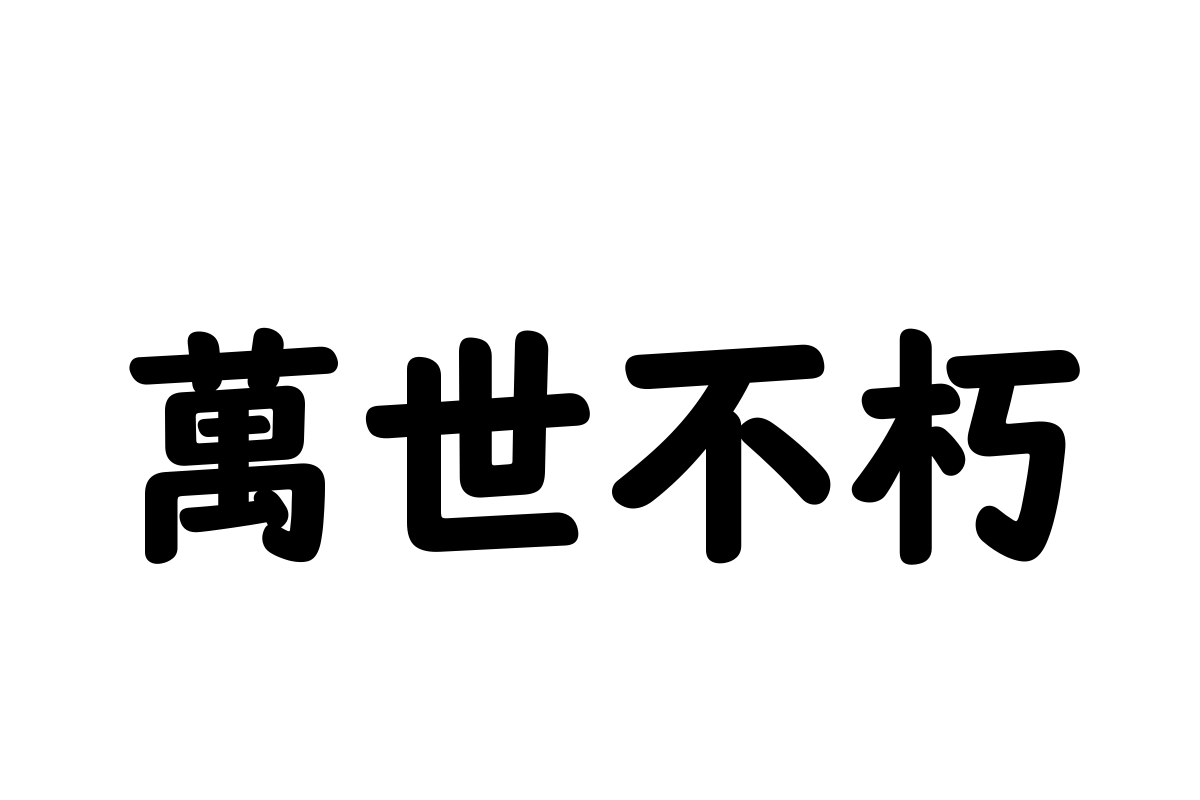
汉仪家书95繁是一款中文字体,由汉仪字库出品。这款字体具有独特的设计风格,笔画流畅自然,字形端正,结构紧凑。它的适用范围广泛,适用于各种印刷品、广告、设计等领域。
汉仪家书95繁的特点如下:
1. 字形端正:汉仪家书95繁的字形结构严谨,笔画清晰,易于阅读和识别。
2. 风格独特:这款字体具有独特的设计风格,线条流畅自然,给人一种优雅的感觉。
3. 适用范围广:汉仪家书95繁适用于各种印刷品、广告、设计等领域,能够满足不同场景的需求。